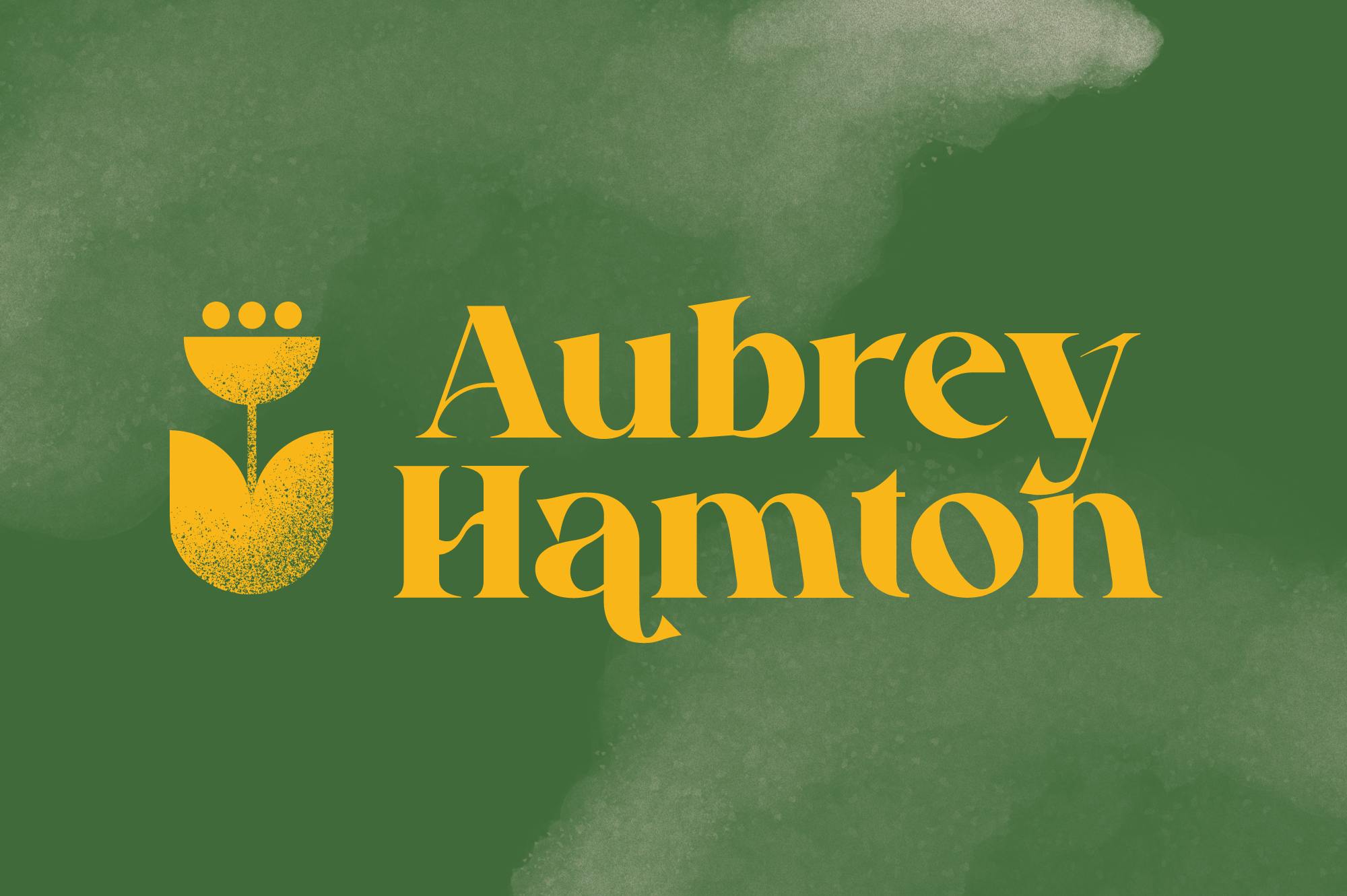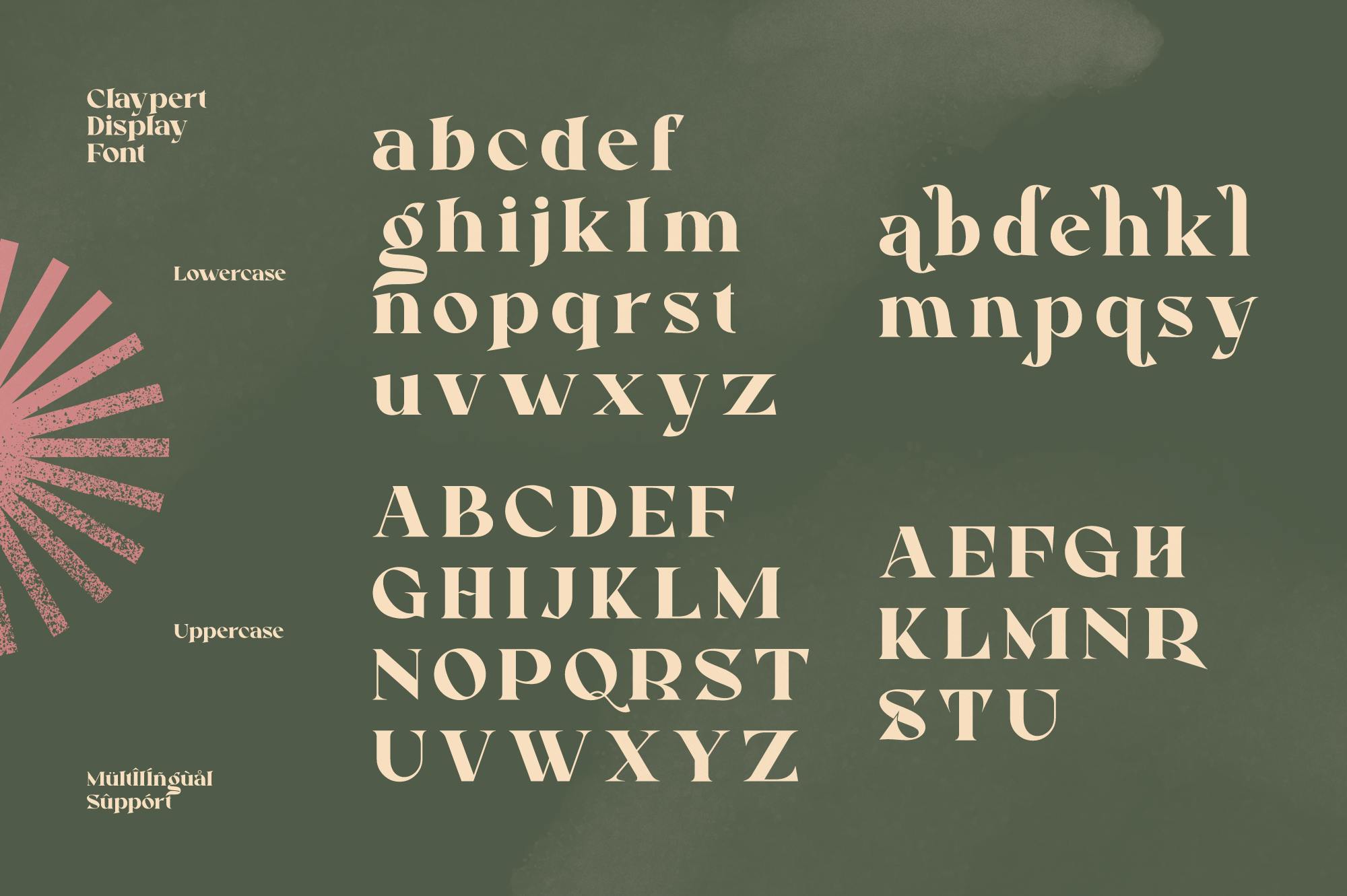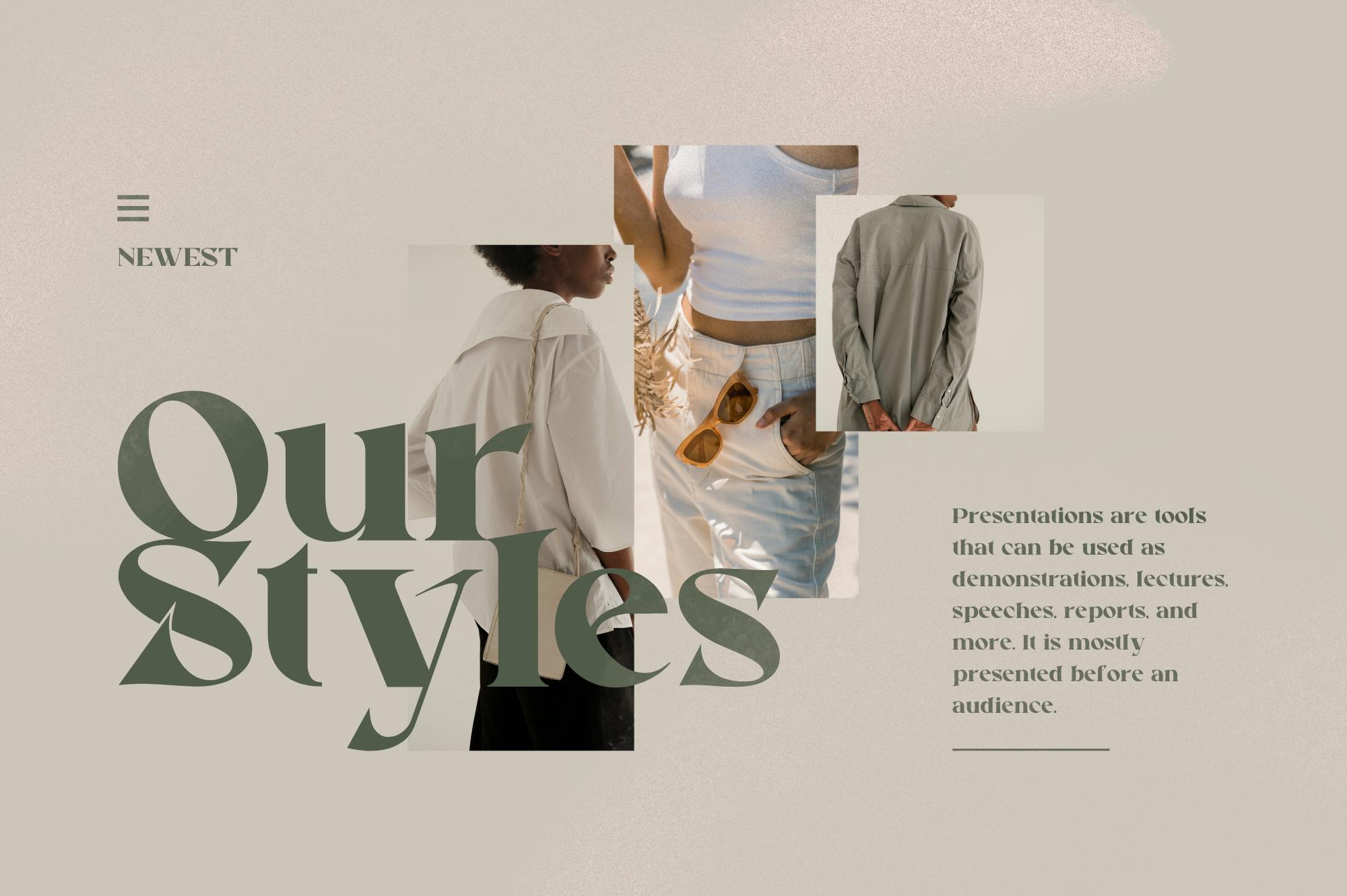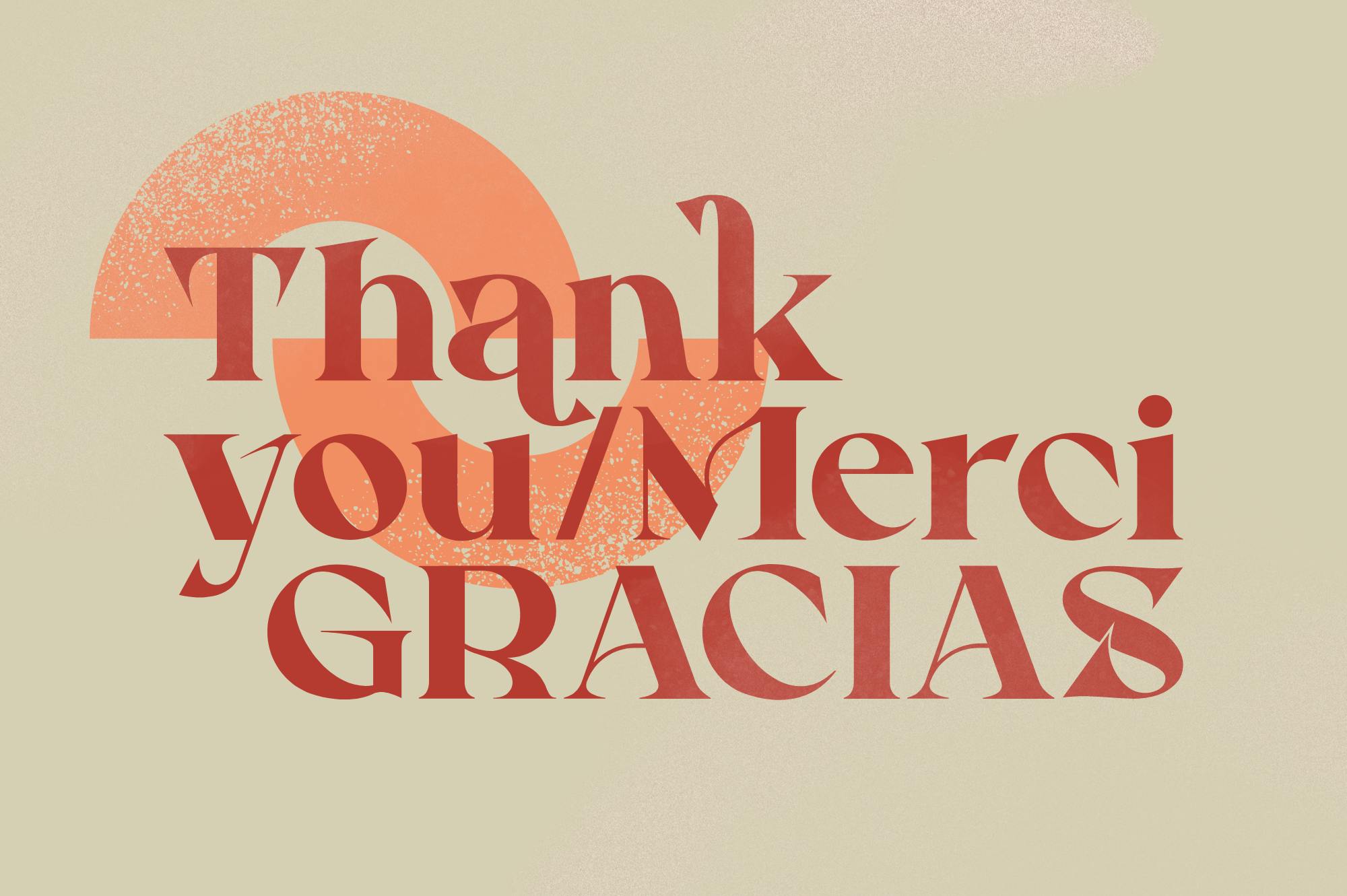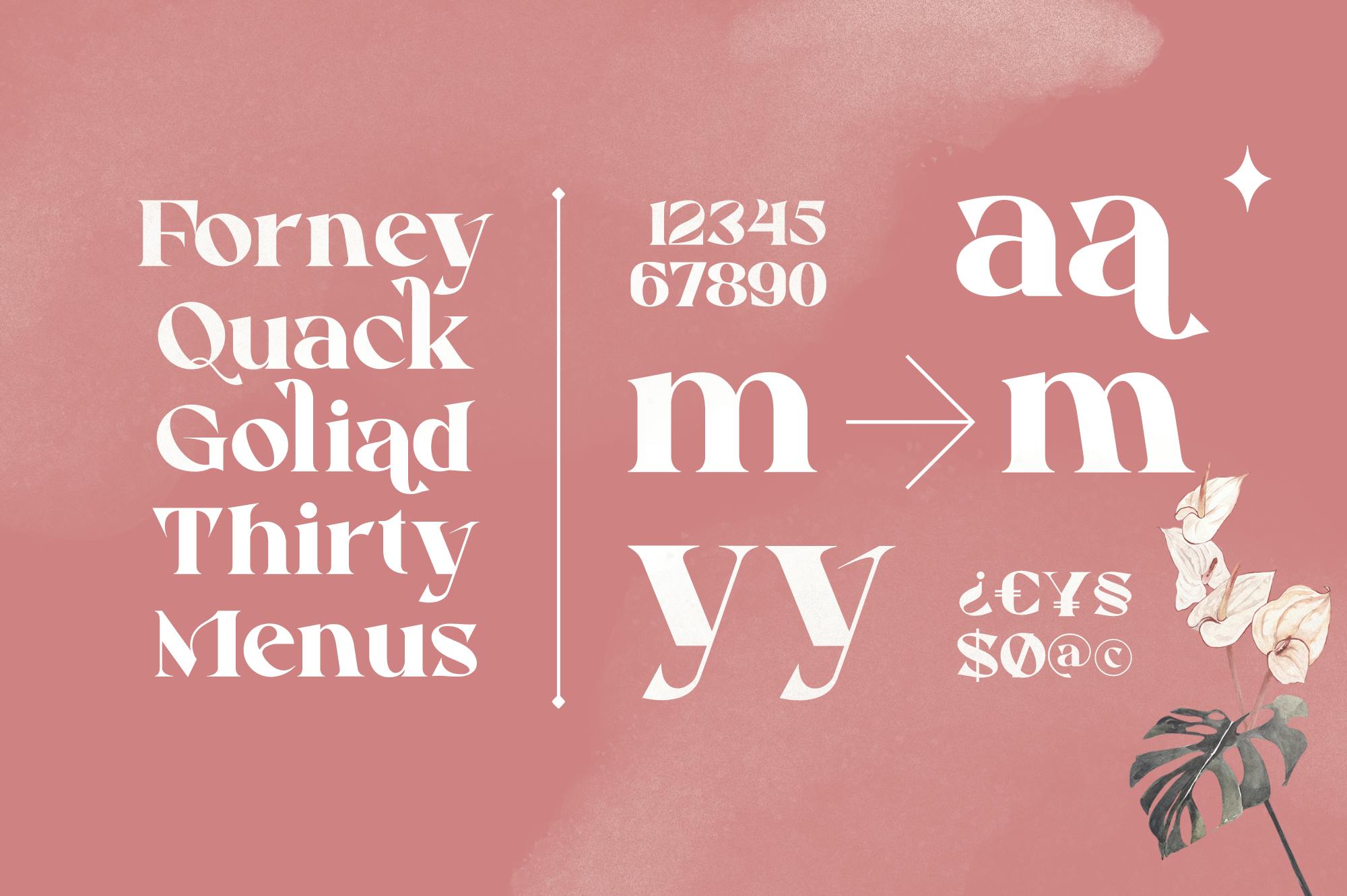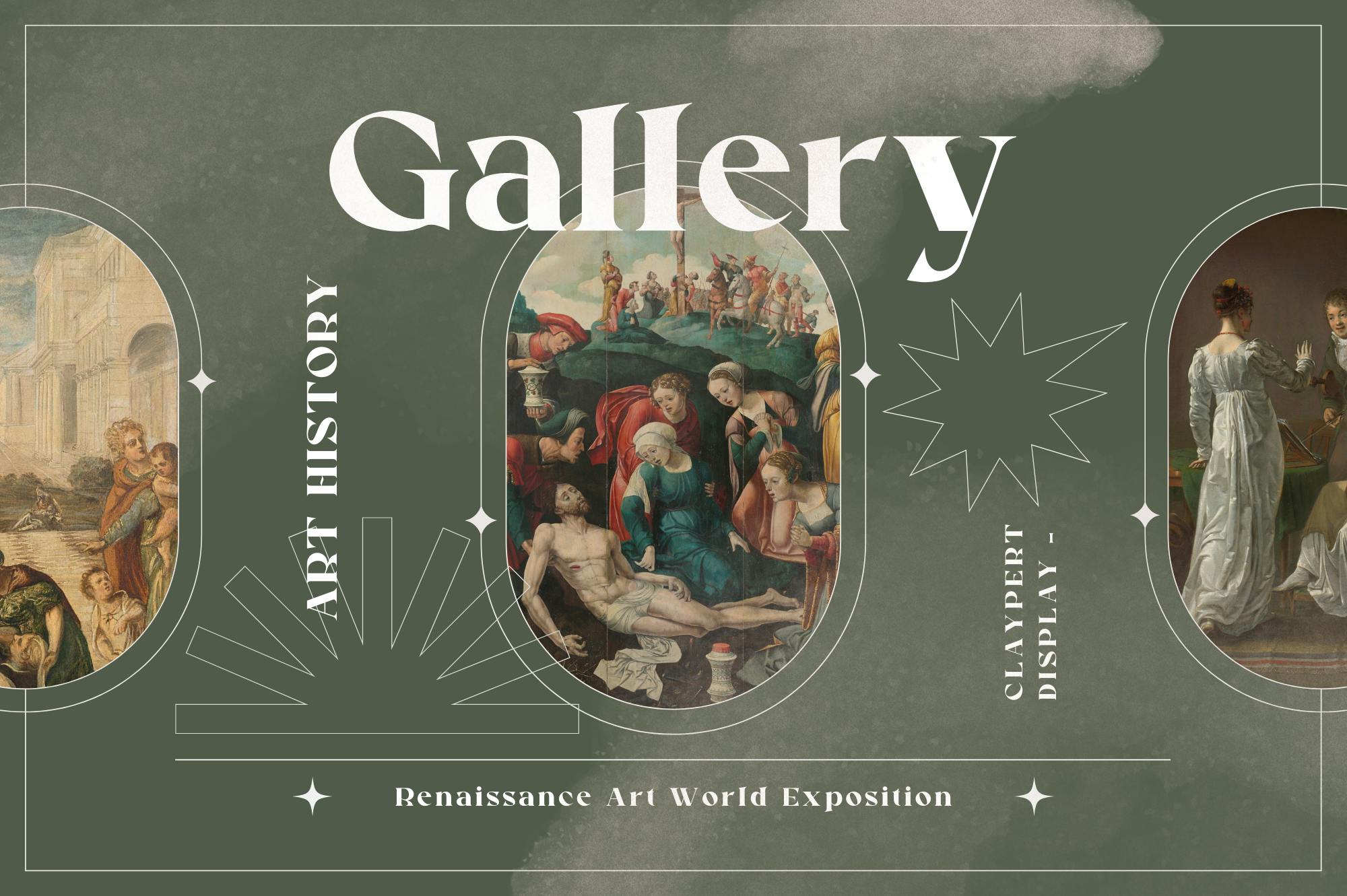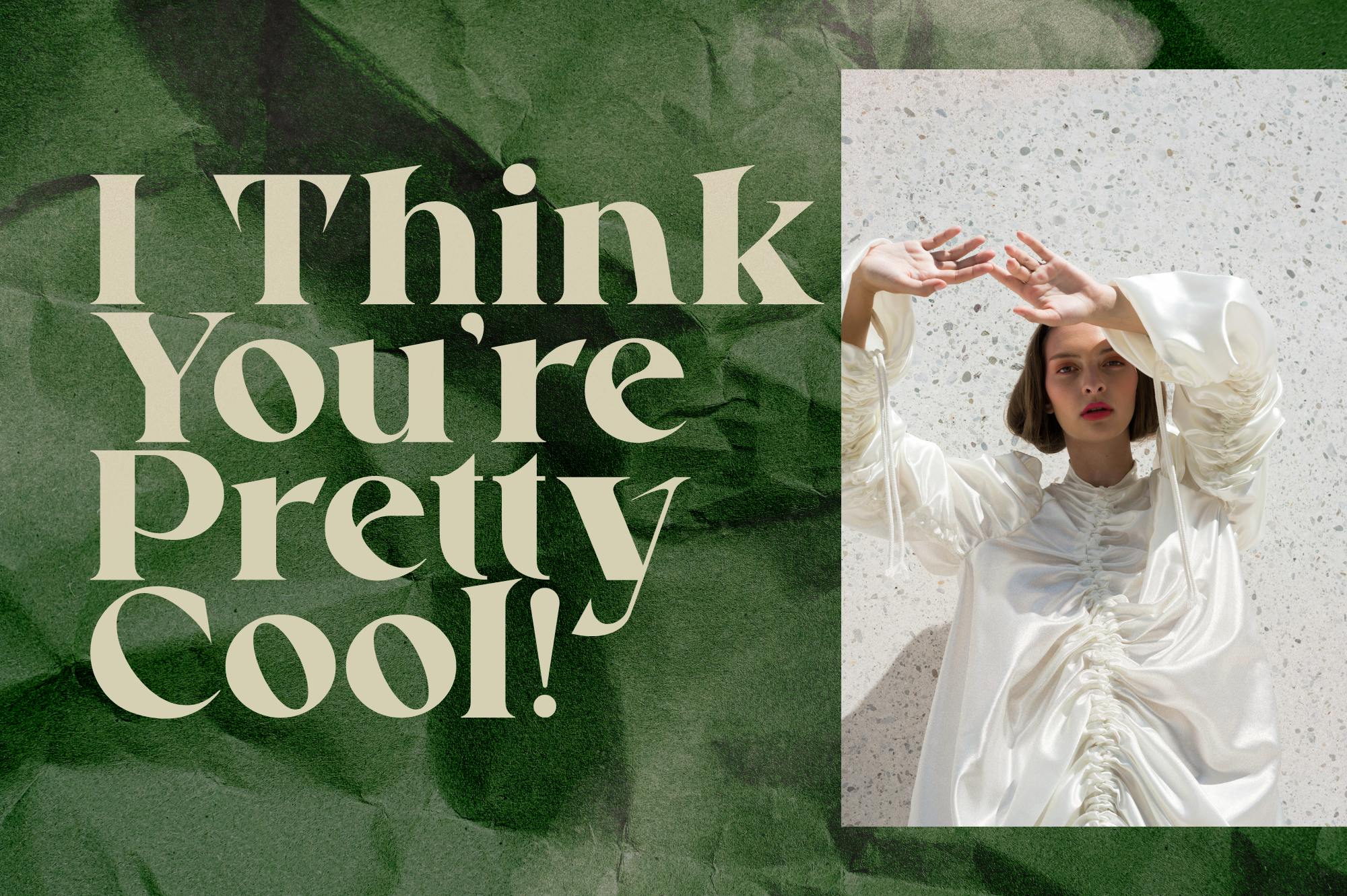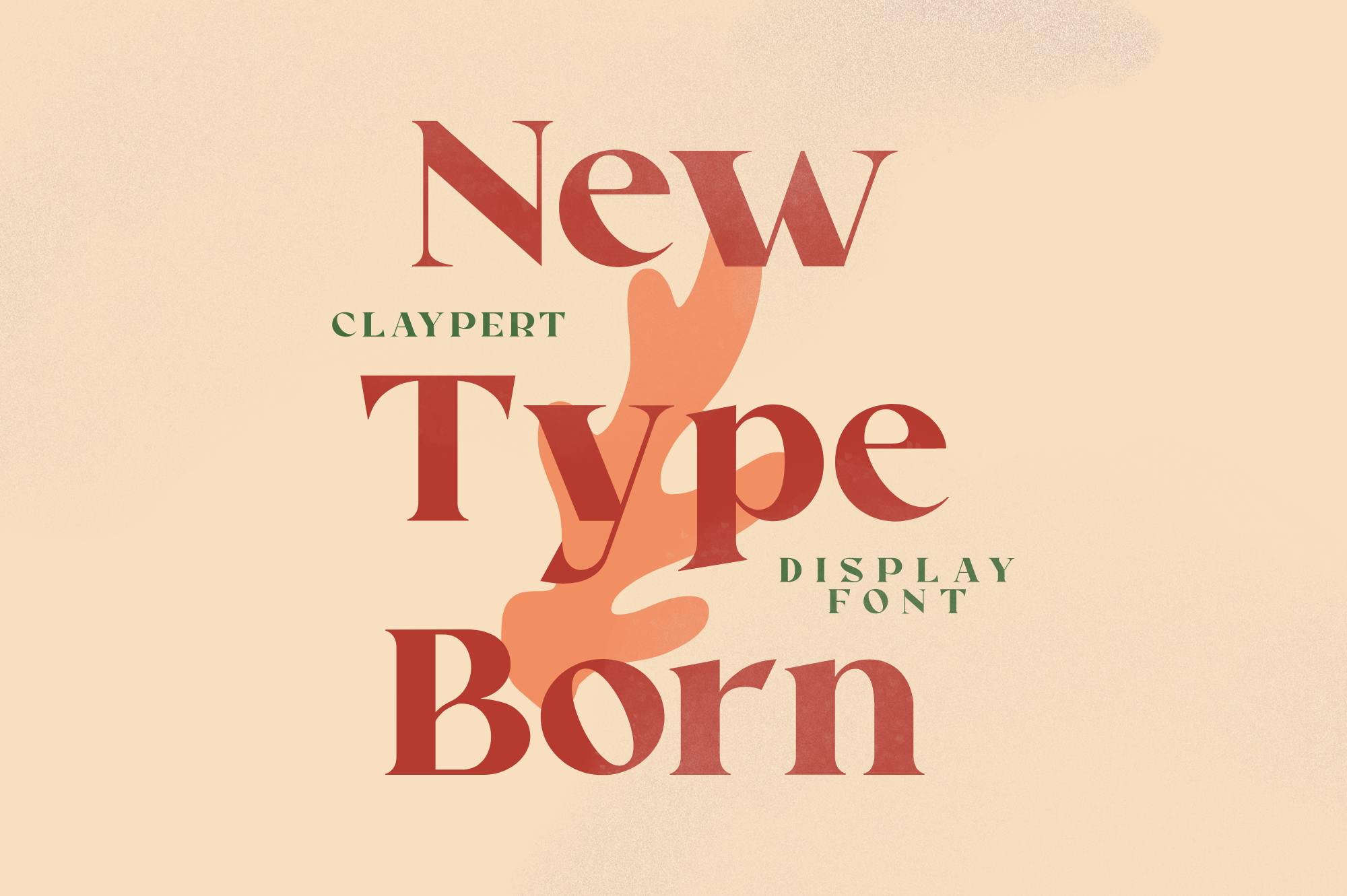
صنعت تایپ، فونت Claypert Display را معرفی میکند؛ این یک فونت زیبا و نمایشی است که از شکلهای ظریف و زیبایی الهام گرفته است. این فونت شامل حدود 256 کاراکتر گلیف است که شامل حروف بزرگ، کوچک، اعداد، نشانهگذاری و گزینههای جایگزین میباشد. با استفاده از این فونت، تأثیر زیبای طراحی شما بیشتر نمایان میشود. این فونت برای ایجاد طرحهای زیبا مانند لوگو، پوستر، مجلات، بروشورها، کارتهای ویزیت و سایر موارد مناسب است.
ویژگیها: